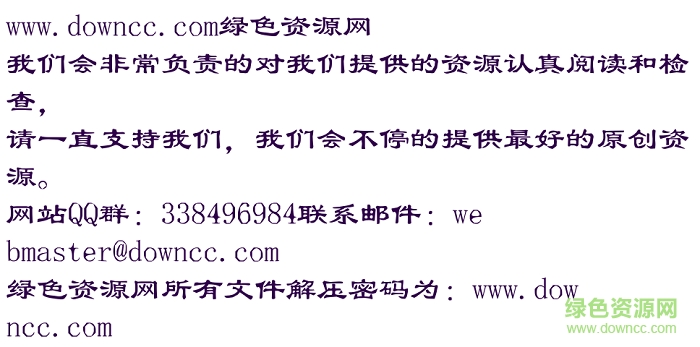
福順小刀隸書字體
福順小刀隸書采用了方勁古拙的隸書特色,飄逸秀麗的形態(tài)給人高雅卻又樸素的沒,讓文字別具一格,喜歡的朋友來綠色資源網(wǎng)搶先體驗吧!
福順小刀隸書字體特色
隸書具有遒勁雄強、飄逸秀麗、工整精嚴、端莊博雅、古樸厚重、奇逸恣肆等風格,而福順小刀隸書取多家所長,納百家之精華,造型獨特而具有章法,方圓兼?zhèn)錃忭嵑闵m合于排版印刷、創(chuàng)意設(shè)計、廣告策劃等多種領(lǐng)域!
福順小刀隸書
隸書亮點